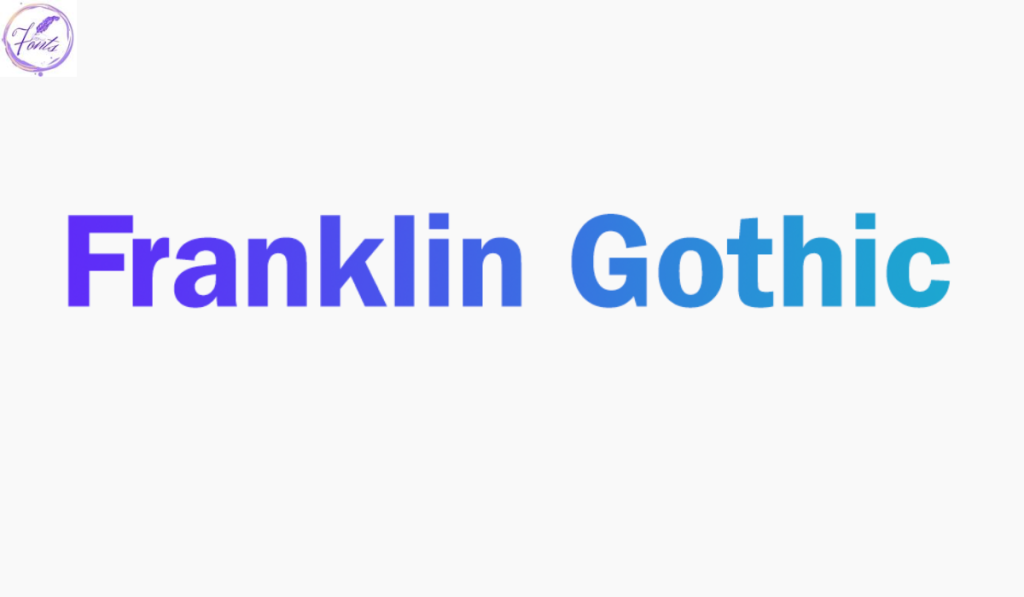
Franklin Gothic font việt hóa
Tác giả: Morris Fuller Benton
Ngày phát hành: 1905
Ngôn ngữ: Tiếng Việt, Tiếng Anh, và nhiều ngôn ngữ khác
Bộ Font: Franklin Gothic
Phân loại: Cá tính, độc đáo
Kiểu chữ: Kiểu chữ không chân
Độ dày: ExtraLight, Light, Regular, Medium, Bold, Black, ExtraBlack
Franklin Gothic font là một trong những phông chữ sans-serif cổ điển được Morris Fuller Benton thiết kế vào năm 1902. Đây là phông chữ thể hiện sự mạnh mẽ và rõ ràng, thường được sử dụng trong báo chí và quảng cáo. Phiên bản việt hóa của Franklin Gothic giúp phông chữ này trở nên phổ biến hơn tại Việt Nam, bổ sung đầy đủ các ký tự tiếng Việt, từ đó mở rộng khả năng ứng dụng của nó trong thiết kế đa ngôn ngữ.
Đánh giá franklin gothic font
Franklin Gothic font được đánh giá cao bởi các tổ chức thiết kế toàn cầu về tính linh hoạt và khả năng đọc cao, đặc biệt là khi sử dụng ở kích thước lớn trên các biển quảng cáo hay tiêu đề. Theo khảo sát của Hội Đồ họa Mỹ, Franklin Gothic nằm trong top các font được yêu thích nhờ vào sự tinh tế và độ bền của kiểu chữ, phù hợp với nhiều mục đích sử dụng khác nhau từ in ấn đến kỹ thuật số.